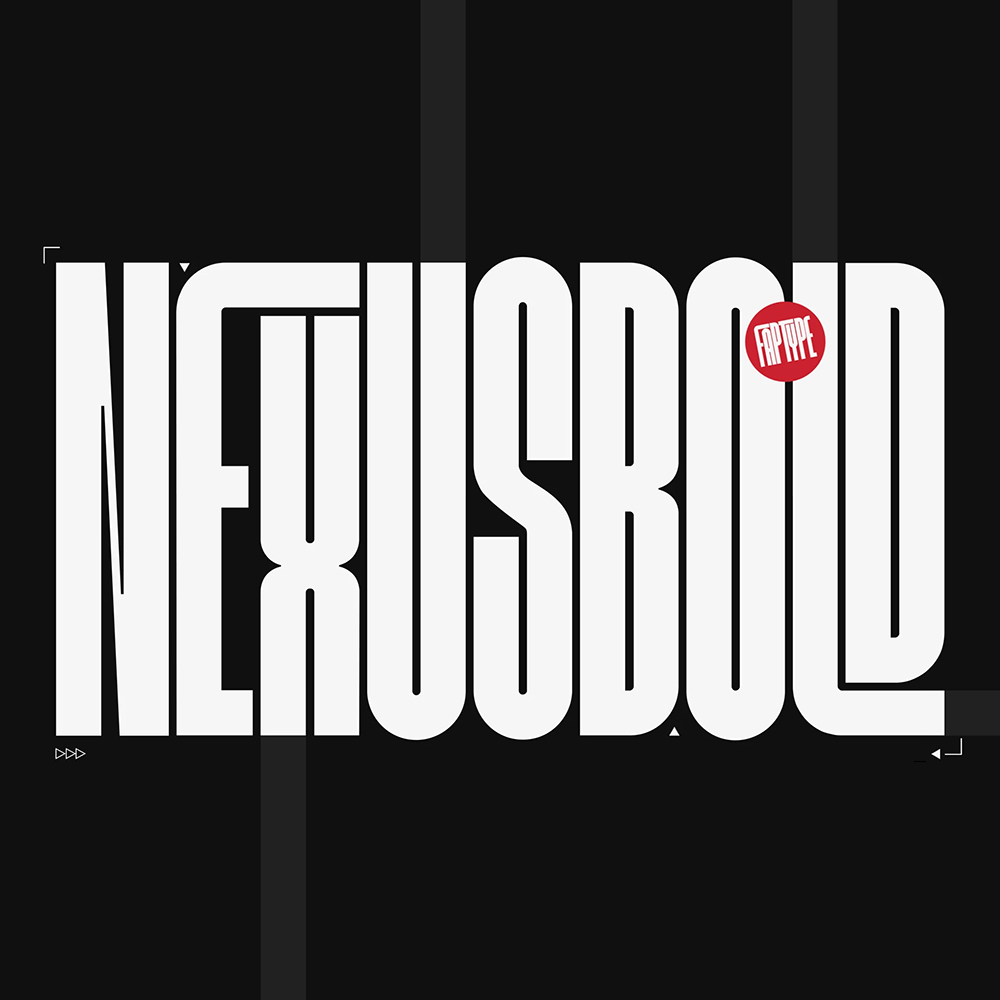
فونت پرمیوم و انگلیسی Nexusbold Font یک فونت مدرن فشرده بدون حروف که تعریف جدیدی از برتری تایپوگرافی ارائه میدهد. Nexusbold با طراحی شیک و معاصر خود، مظهر ظرافت و کارایی است که با مجموعهای گسترده از لیگاتورهای دقیق ساخته شده، تقویت میشود. فرم فشرده Nexusbold با دقت ساخته شده است تا فضا را بدون به خطر انداختن خوانایی بهینه کند. چه در حال ایجاد تیتر، لوگو، بستهبندی یا طراحی وب باشید، ساختار جمع و جور این فونت، تأثیر بصری چشمگیری را تضمین میکند که توجه را به خود جلب میکند.